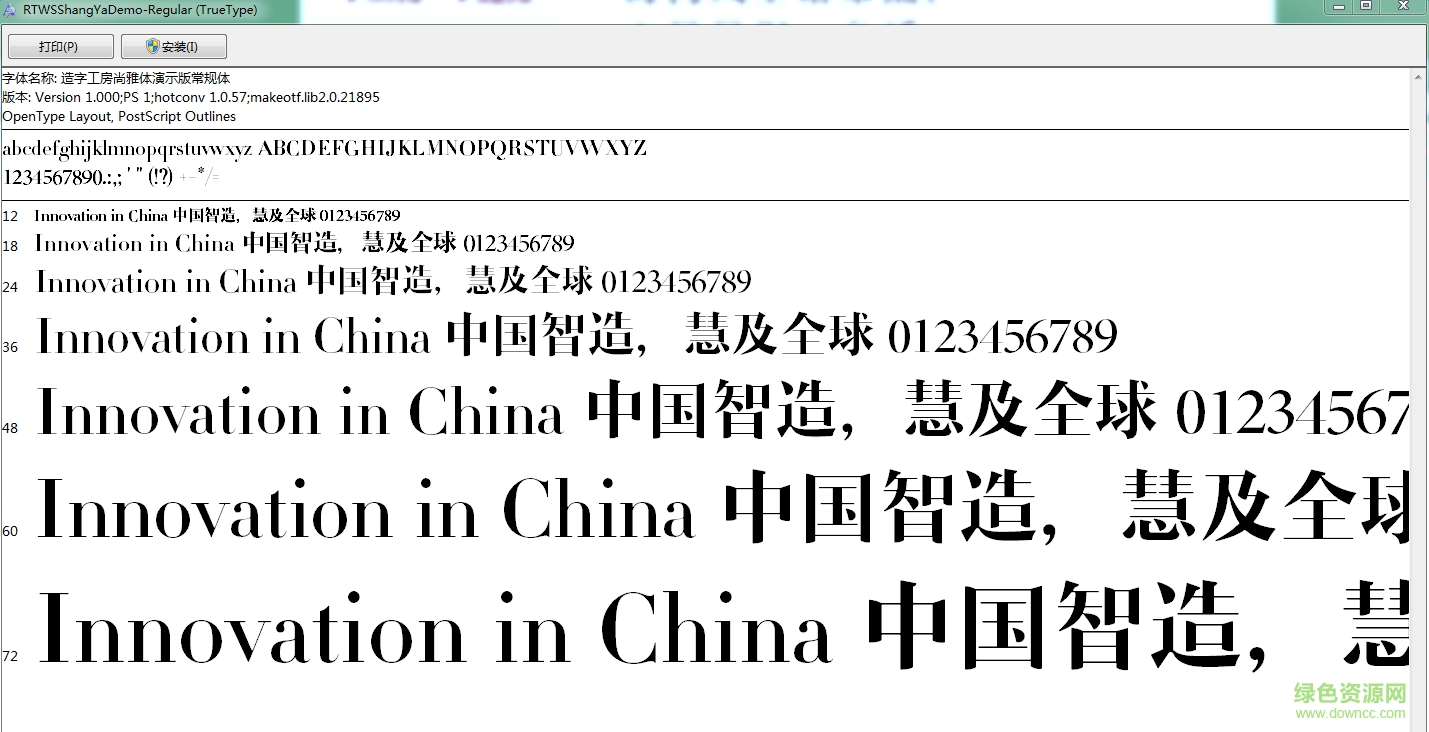
造字工房尚雅體演示版常規(guī)體是一款造字工房類時(shí)尚現(xiàn)代風(fēng)格字體軟件,尚雅體演示版常規(guī)體給人非常正式的感覺,非常適合用于工作項(xiàng)目以及各種演示場合,也深受廣大書法家的喜愛,還有更多好看字體盡情期待,歡迎到綠色資源網(wǎng)下載體驗(yàn)!
造字工房尚雅體演示版常規(guī)體是一款用于網(wǎng)頁設(shè)計(jì)方面的字體,筆畫設(shè)計(jì)簡潔、筆鋒柔和典雅,相比傳統(tǒng)宋體,更有多項(xiàng)個(gè)性化創(chuàng)新設(shè)計(jì)。此款字體用途廣泛,主做標(biāo)題與副標(biāo)題之用。